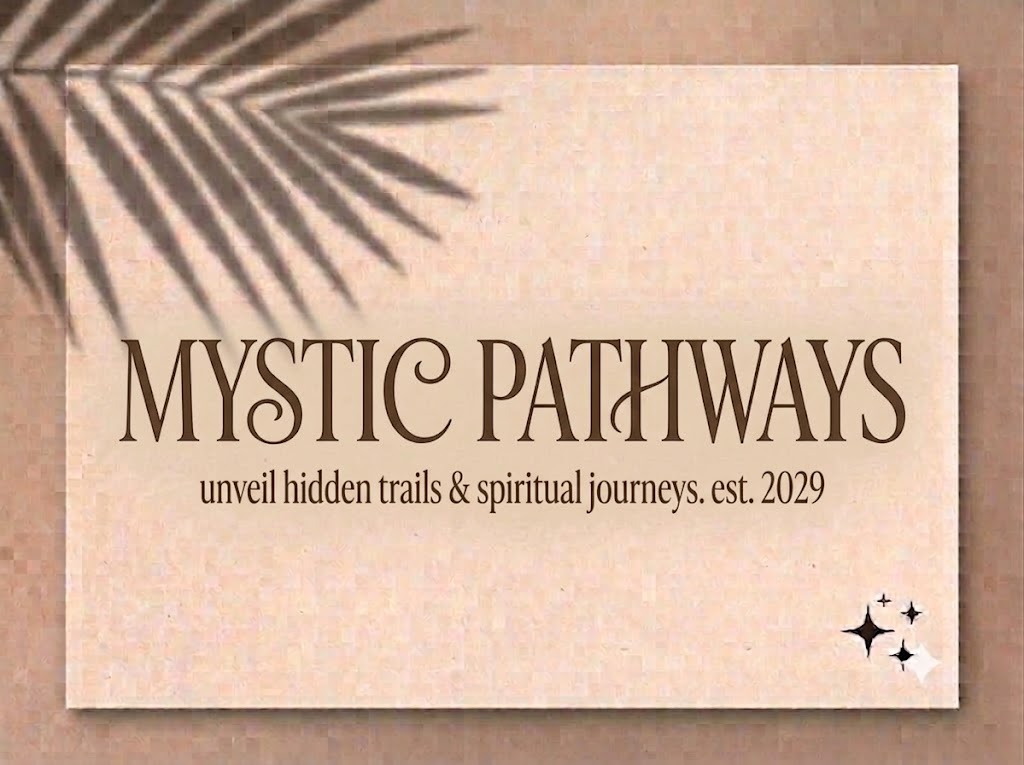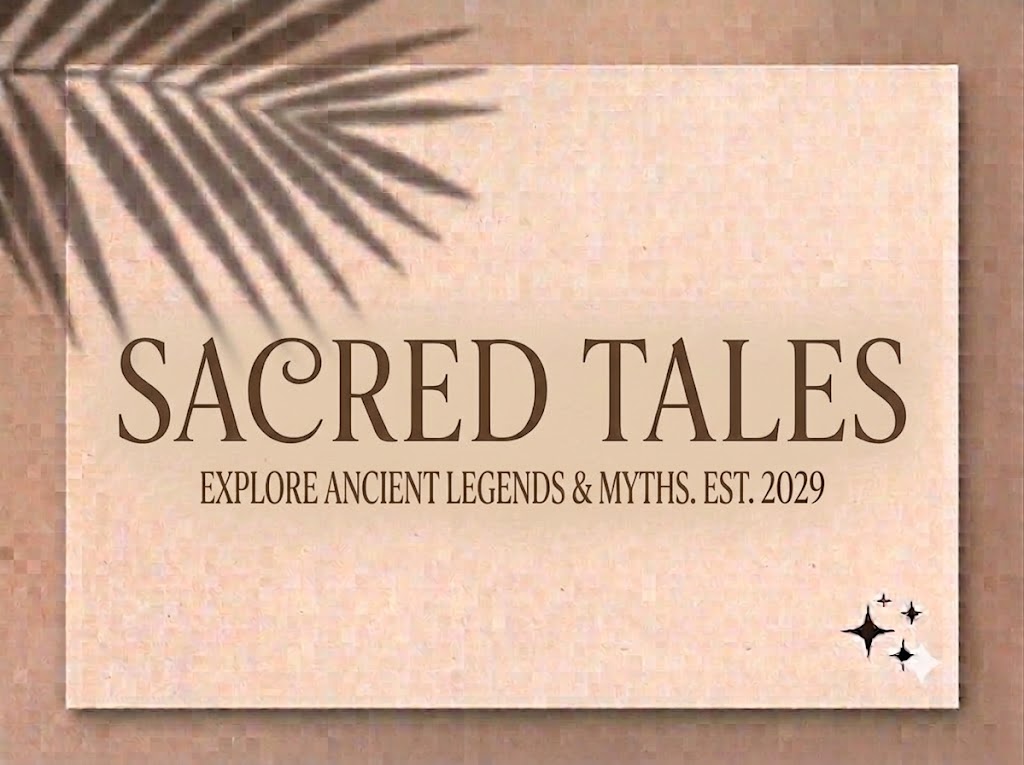
1FTV VIP Alisheia
Trong phân khúc thiết kế cao cấp, xu hướng tối giản kết hợp với các đường nét có chân thanh lịch luôn là sự lựa chọn hàng đầu để khẳng định đẳng cấp của một thương hiệu.
Những nét chữ có độ tương phản thanh đậm rõ rệt không chỉ mang đến chiều sâu nghệ thuật mà còn tạo nên một giao diện thị giác vô cùng xa xỉ, cuốn hút người xem ngay từ cái nhìn đầu tiên.
Nếu bạn đang tìm kiếm một phông chữ display quý phái để làm nhận diện thương hiệu thời trang, mỹ phẩm hoặc làm tựa đề cho các thước phim nghệ thuật, thì font 1FTV VIP Alisheia chính là một kiệt tác không thể bỏ qua.
Giới thiệu về font 1FTV VIP Alisheia
Font 1FTV VIP Alisheia là một bộ chữ hiển thị có chân (serif) mang phong cách tân cổ điển đầy kiêu sa, sang trọng và đậm chất thời trang cao cấp.
Tác phẩm này được hoàn thiện chỉn chu ngay ở phiên bản đầu tiên Version 1.000, mang đến sự nhất quán hoàn hảo trong từng đường nét cấu trúc của toàn bộ hệ thống ký tự.
Nhờ những thông số kỹ thuật tối ưu này, phông chữ đảm bảo khả năng hiển thị vô cùng mượt mà, sắc nét, giúp các nhà thiết kế tự tin ứng dụng trên các phần mềm đồ họa chuyên nghiệp mà không lo lỗi vỡ nét hay răng cưa khi phóng lớn.
Đặc điểm nổi bật của phong cách thiết kế VIP Alisheia
Sức hút mê hoặc của font 1FTV VIP Alisheia đến từ cấu trúc chữ cao ráo kết hợp tài tình với độ tương phản thanh đậm cực kỳ sắc sảo.
Phần chân chữ (serif) được gọt giũa mảnh mai nhưng vô cùng dứt khoát, kết hợp với các đường cong uốn lượn mềm mại ở các ký tự như c, e, s, g, tạo nên một tổng thể vừa vững chãi, vừa uyển chuyển như những tác phẩm điêu khắc nghệ thuật.
Khác với các dòng font tiêu đề thông thường chỉ hỗ trợ chữ viết hoa, 1FTV VIP Alisheia tích hợp trọn vẹn cả hệ thống chữ cái thường lẫn chữ viết hoa đồng bộ.
Tiện ích này giúp bạn dễ dàng phối hợp hoa – thường một cách linh hoạt, tạo nhịp điệu đọc tự nhiên, thoáng đãng và mang đậm tinh thần của các tạp chí thời trang danh tiếng thế giới.
Để phông chữ vận hành hoàn hảo trên mọi hệ điều hành, phiên bản font 1FTV VIP Alisheia đã trải qua quy trình xử lý thông số kỹ thuật nội tại vô cùng khắt khe.
Hệ thống khoảng cách chữ (kerning) và độ giãn dòng (tracking) đã được căn chỉnh chuẩn xác đến từng pixel, giúp các nét thanh nét đậm khi đứng cạnh nhau luôn giữ được khoảng trống thẩm mỹ lý tưởng mà không bị dính nét.
Bên cạnh hệ thống chữ cái hoa và thường đồng bộ, phông chữ còn tích hợp đầy đủ dãy số từ 0-9 cùng hệ thống các ký tự đặc biệt, dấu câu thông dụng (1234567890.:,;'"(!?)+-*/=).
Bản Việt hóa chuẩn chỉnh này giúp các nhà sáng tạo nội dung hoàn toàn yên tâm thiết kế các văn bản tiếng Việt có dấu mà không lo gặp phải tình trạng nhảy font, lỗi hiển thị hay thiếu ký tự khi gõ.
Hình ảnh demo thực tế của font 1FTV VIP Alisheia
Để giúp bạn dễ dàng đánh giá khả năng co giãn và hiển thị linh hoạt của phông chữ này trên các kích thước khác nhau, hãy cùng xem qua bảng mô phỏng từ file hệ thống image_5f07dd.png:
Kích thước nhỏ (12pt – 24pt): Dù sở hữu các nét thanh siêu mảnh, cấu trúc chữ và dấu tiếng Việt vẫn hiển thị rõ ràng, ngay ngắn, cực kỳ dễ đọc trên màn hình thiết bị di động.
Kích thước lớn (36pt – 72pt): Đây là đất diễn hoàn hảo nhất để font chữ phô diễn toàn bộ sự kiêu sa, quý phái, tạo tác động thị giác mạnh mẽ chiếm trọn tâm trí người xem cho các dòng headline chính.
Ứng dụng của font VIP Alisheia trong thiết kế đồ họa và làm video
Sở hữu nét cá tính sang trọng và cấu trúc hoa – thường tinh tế, font 1FTV VIP Alisheia mở ra không gian ứng dụng vô cùng rộng lớn cho các dự án truyền thông cao cấp:
Làm tiêu đề mở đầu cho video ngắn (TikTok, Reels, Shorts): Kiểu chữ serif thanh lịch này cực kỳ ăn nhập với các video cinematic, vlog phong cách sống, thời trang hoặc lookbook, giúp cụm tiêu đề chính nổi bật một cách tinh tế trên khung hình đứng 9:16 nhằm giữ chân người xem lướt chậm lại.
Thiết kế bìa tạp chí, Lookbook và Poster thời trang: Hoàn hảo cho các ấn phẩm truyền thông thuộc lĩnh vực thời trang, mỹ phẩm, trang sức xa xỉ, kiến trúc hoặc các triển lãm nghệ thuật sang trọng.
Ảnh thu nhỏ YouTube (Thumbnail) phong cách nghệ thuật: Đặc biệt hiệu quả với các kênh làm nội dung về âm nhạc acoustic, chữa lành, review sách, phim ảnh hoặc chia sẻ kiến thức chuyên sâu cần chiều sâu học thuật và sự tin cậy.
Nhận diện thương hiệu phong cách luxury: Phù hợp làm logo dạng chữ, biểu ngữ quảng cáo, menu nhà hàng cao cấp, thiệp mời sự kiện VIP hoặc thiết kế nhãn mác cho các thương hiệu nước hoa, spa cao cấp.